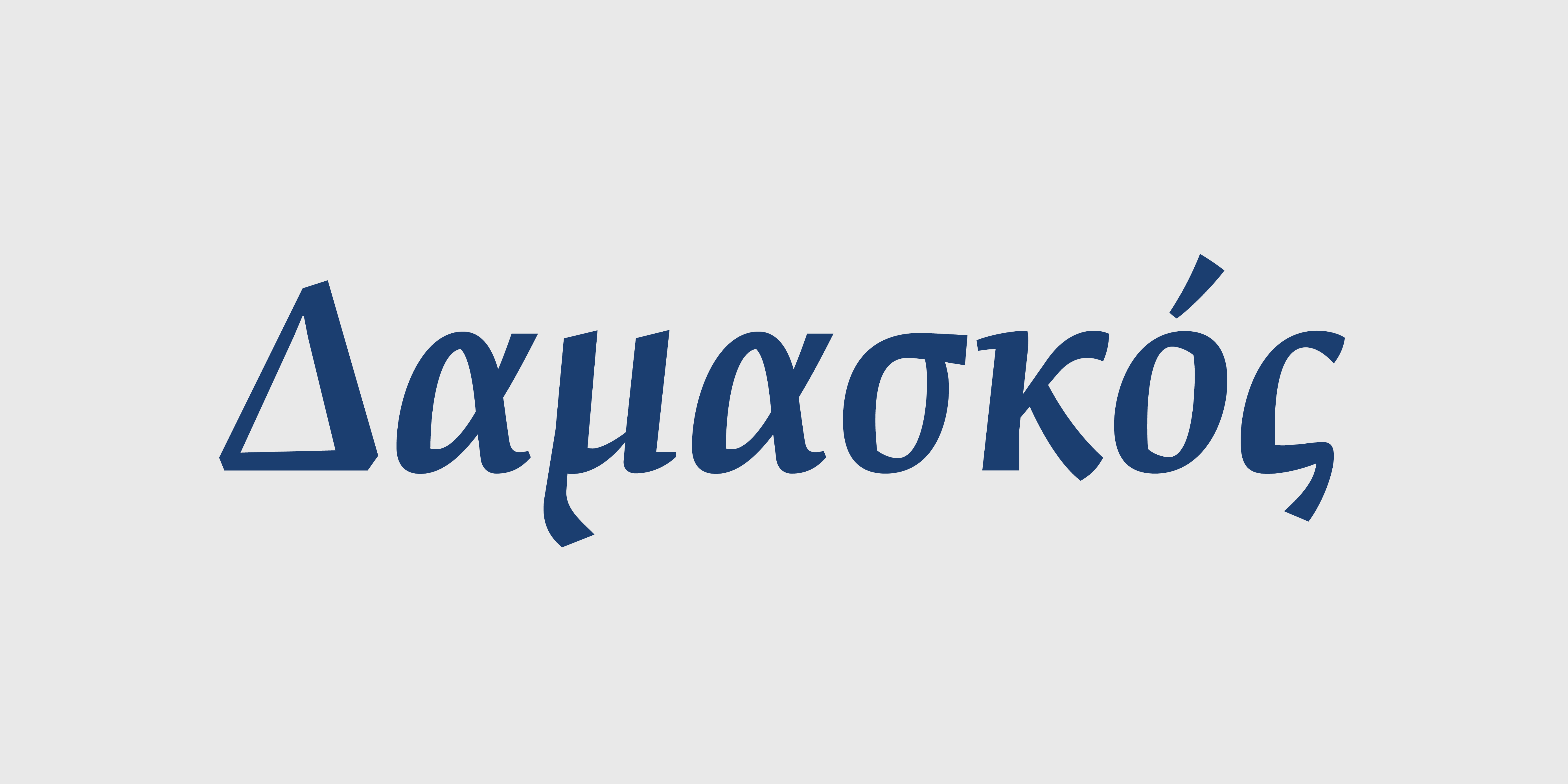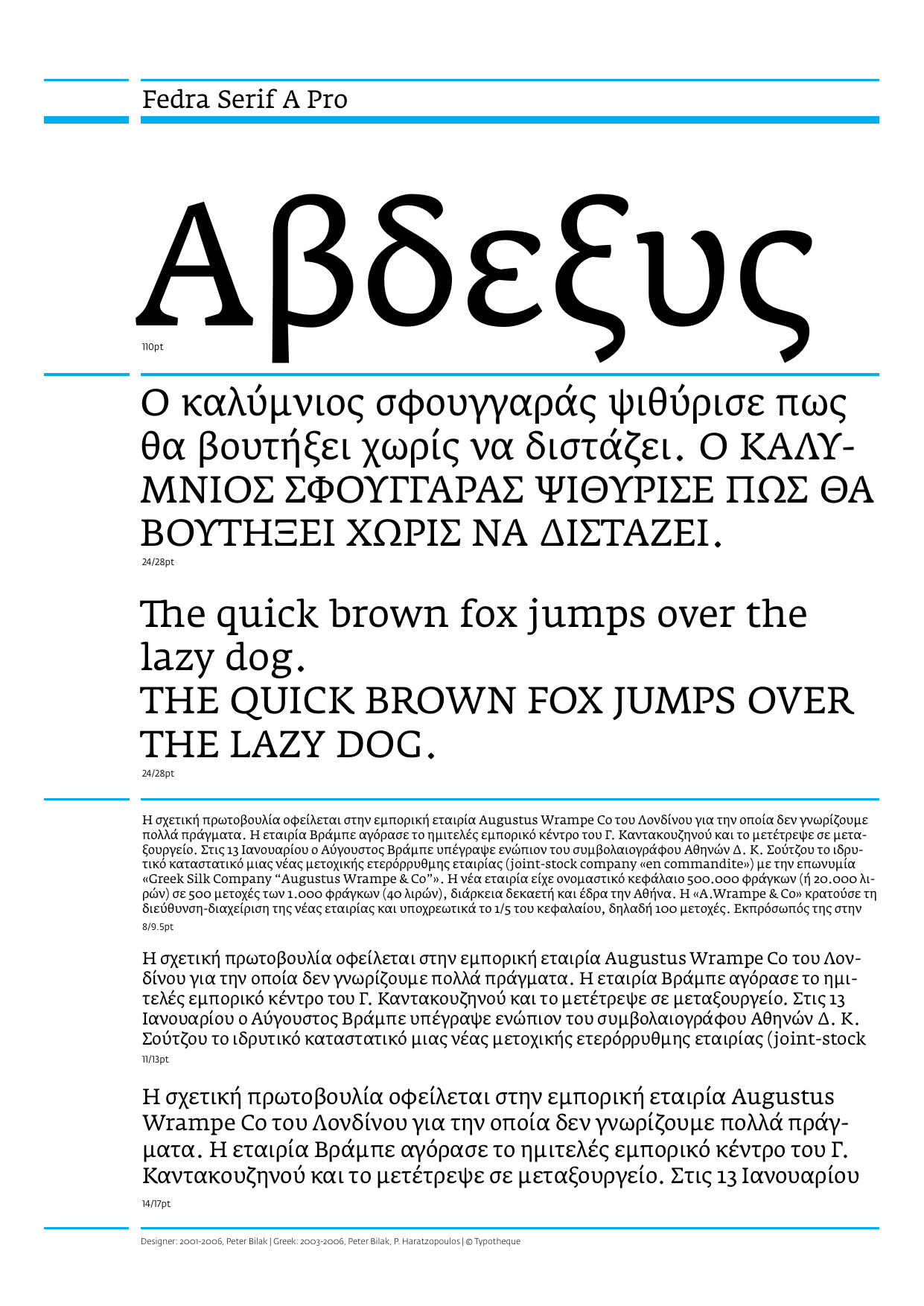
Fedra Serif Pro Collection
Fedra Serif A Pro
Fedra Serif B Pro
Αντί να αναζητά έμπνευση στο παρελθόν, η Fedra Serif είναι μια σύγχρονη, πολυσύνθετη γραμματοσειρά όπου η αισθητική και τεχνολογική πλευρά της είναι συνδεδεμένες. Η Fedra συνδυάζει φαινομενικά αντιφατικούς τρόπους σχεδίασης σε μια απόλυτα, όμως, αρμονική γραμματοσειρά. Οι ανθρωπιστικές της καταβολές (χειρόγραφος ρυθμός); ισορροπούν με τον ορθολογικό σχεδιασμό (τραχύς κάνναβος στην οθόνη του υπολογιστή);. Η Λατινική και η Ελληνική Fedra σχεδιάστηκε σχεδόν ταυτόχρονα και η μία επηρέασε την άλλη, όχι μόνο τα Λατινικά προς τα Ελληνικά αλλά και αντίστροφα. Το αποτέλεσμα είναι μια αυτόνομη χειραφετημένη ελληνική γραμματοσειρά διαθέσιμη σε μονοτονική αλλά και σε πολυτονική μορφή. Η εκδοχή Α ταιριάζει στις αναλογίες της Fedra Sans, με μεγάλο ύψος πεζών (x-height); και μικρά ανωφερή. Η εκδοχή Β έχει αυξημένο κοντράστ και επιμηκυμένα ανωφερή, γεγονός που την κάνει ιδανικότερη για εκτυπώσεις υψηλής ανάλυσης ή χρήση σε μεγαλύτερες στιγμές γραμμάτων. Ο συνδυασμός αυτών των παραλλαγών έχουν σαν αποτέλεσμα μια γραμματοσειρά ικανή να δώσει λύσεις σε περίπλοκα τυπογραφικά προβλήματα. Σχεδιαστής Peter Bilak, Ελληνική έκδοση, Παναγιώτης Χαρατζόπουλος.